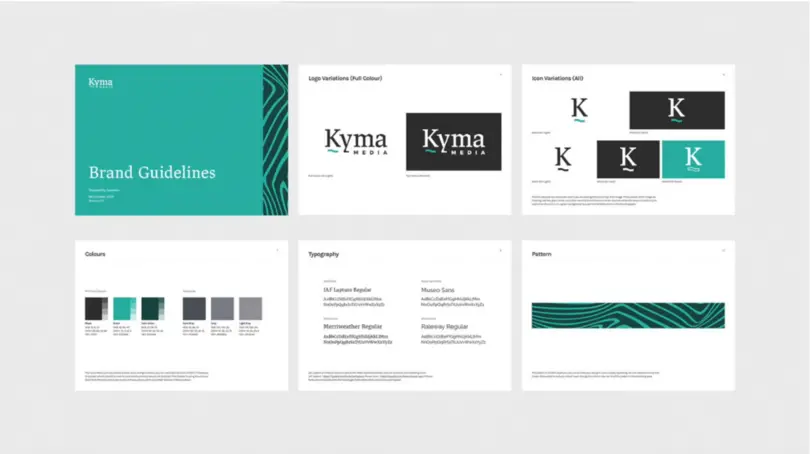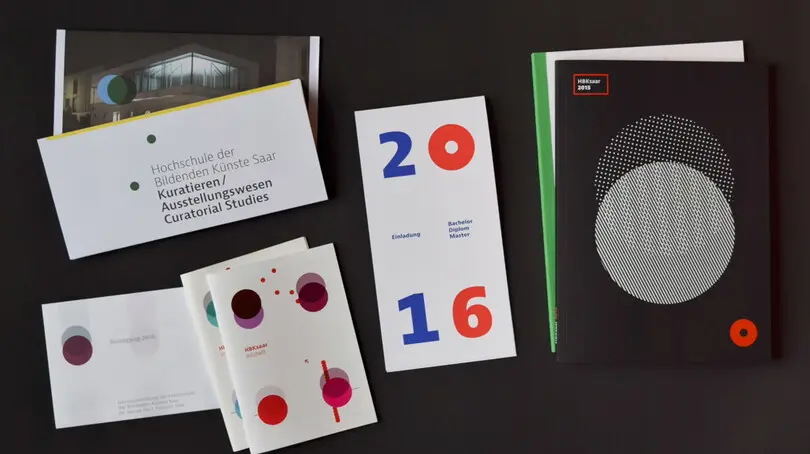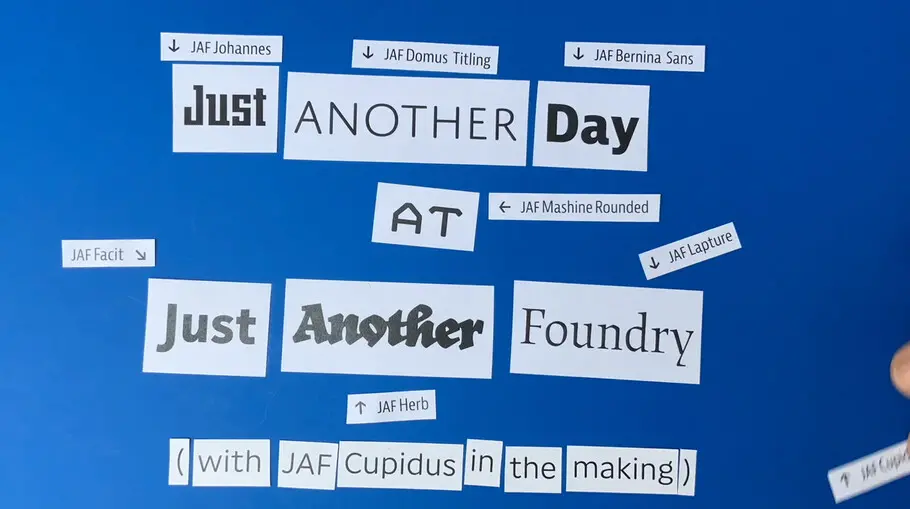
組織のメッセージを企業の声として伝えるツール
コーポレートフォント(企業専用書体)
ドイツのミュンヘンでティム・アーレンス氏とタイプファンダリー「Just Another Foundry」(以下、JAF)を運営し、書体開発や欧文組版の仕事をされている麥倉聖子氏のプレゼンテーション。武蔵野美術大学卒業後、イギリスのレディング大学で欧文タイポグラフィを学びました。
今回のテーマであるコーポレートフォント(企業専用書体)は、組織のメッセージを伝えるツールで、いわばその企業の声のようなもの。欧州でも広く使われており、ドイツではメルセデスベンツやルフトハンザなどが有名です。企業や組織のブランドアイデンティティを決めるときにデザインの一環として特定の書体を指定して、すべてのマーケティングに使うことが一般的になっています。
セッションの冒頭では、JAF が制作したフォントやコーポレートフォントを紹介。
Kyma Media Branding のコーポレートフォントには、JAF Lapture というブラックレターを取り入れた書体が使われています。
また、お茶のブランド Klenk では、ラウンドサンズの JAF Domus を使用。企業ロゴだけでなく、Webサイトやカタログ、説明文にも使われているそうです。
Germany Trade & Invest ドイツの経産省 GTAI のアイデンティには、JAF Bernina Sans とニュージーランドの書体デザイナー、クリス・ソワーズビーさんの書体 Tiempos を使用。
ドイツの美術大学 HBKsaar のアイデンティティ。JAF Bernina Sans を専用書体として使用。かっこよく使ってくれていて、制作物を見るのが楽しみだそうです。
コーポレートフォントの利用は欧州ではとても一般的。大企業に限らず浸透しているそうです。しかし、コーポレートフォントがあるから大丈夫というわけではありません。コーポレートフォントを見つけることは、結婚するパートナーを見つけることに似ています。結婚式と結婚生活が違うように、コーポレートフォントを見つけることと運用することは別問題なのです。
コーポレートフォントの運用の問題点はこちらの4点。
1. コーポレートフォントと全然合わないシステムフォントを併用して使っている
2. 新旧フォントが混在
3. 印刷物はがんばっているのに Webサイトにはフリーフォントを使っている
4. 組版に問題あり
1は運用する人がデザイナーではない場合、専用書体ですべてカバーできない場合(例えば、長文で使えないなど)に起こる問題。運用が始まる前にシステムフォントを決めておくとよいそうです。
2は比較的大きな組織で、アートディレクターがいない場合によく起こる問題。
3は Webフォントの初期にはユーザーが使いたくても価格的に手が出なかったこともありましたが、今は価格的に安定したこと、オンラインマーケティングの重要性が理解されてきたこともあり、改善されつつあります。
4はいろいろなケースが見られます。
• 字間や単語間のスペーシングの設定がまずい(字間が空きすぎ、単語間がつまりすぎ)
• 行間や行長の設定がまずい(行間が詰まりすぎ、行が長すぎ)
• 行末処理ができておらず、ガタガタで読みにくい(行末が飛び出している、1単語残ってしまっている)
• リガチャー(合字)やコンテクスチュアル・オルタネート(文脈に応じて別の文字に自動的に切り替わって表示される機能)が使いこなせていない
• 書体のチョイスが組まれた文章のチョイスにあっていない
• ダーシや引用符の間違った使用(間抜け引用符、ダーシのかわりにハイフンが使われている)
• 大文字、小文字の使い分けの間違い(人名が全部大文字になっているなど)
• ハイフンの位置の設定が間違っている(child-like なのに chil-dlike で切れている)
欧文組版のミスをさらに細かく分別すると、以下の3タイプに分けられます。
A:欧州の組版初心者でも絶対にしないミス
• 大文字小文字の使い分けの間違い(小学校で習うのでネイティブは間違えない)
• ハイフンの位置の間違い(ソフトウェア上で自動設定されているので間違えない)
B:欧州の組版初心者がよくするミス
• ダーシや引用符の間違った使用
• イタリックの間違い
• 行末処理がガタガタ
• 書体のチョイスにもう一工夫
C:欧州のデザイナーでもしてしまうミス
• 字間や単語間の設定がまずい
• 行間、行長の設定がまずい
• リガチャーやコンテクスチュアル・オルタネートが使えていない
Aは表記法の領域、Bは見た目の領域に近く、同じミスでもAのミスとBのミスは質が違います。Cは経験を積むうちにうまくなります。
重要なポイントをまとめると、読み手にとって重要なのはAの表記法の領域のミス。ここがクリアできないと専用書体を使っていても現地の人は絶対に「おかしい」と気づきます。
そこを最低のボーダーラインとして覚えておくとよいでしょう。
イギリスとドイツのタイポグラフィの傾向の違いはありますか?
(麥倉氏)ドイツの方が組版のレベルが高いように思います。学校でスキルを身につけてから社会に出ているからでしょうか。イギリスの大学はアート寄りのところが多いのが原因かもしれません。
(小林)同感です。ドイツの地方紙の記者が書体のことをすごくよく知っていました。一般人レベルでもよく知っていますね。
グラフィック寄りの仕事でも組版には気をつけるべきでしょうか?
今回は文章、本文組のお話をしましたが、ポスターや広告などは別です。ルールにとらわれずに自由に制作していいと思います。
欧文書体を学ぶにあたり感銘を受けた書籍は?
(麥倉氏)どれが一冊というのはないのですが、東ドイツのタイポグラファー、アルバート・カパの本がいいですね。
(小林)本よりも街中で見かける文字、手を使って生み出したものの力はすごいと思います。なぜ Type& で石彫やカリグラフィの話をするのかと言うと、定規を使わず有機的な線を出すとどう見えるのかを考えている人が話す言葉には説得力があるからです。普段から目を使って見ていると、目が鍛えられているから気づく。文字の見え方に対するセンスを養うことにつながります。本を読んだからわかるということではないのです。
(麥倉氏)3年くらい前からカリグラフィを始めてみて、もっと理解することができました。すぐうまくならないかもしれませんが、目が鍛えられます。
(小林)文字の中に宿る力、定規を使わないで書くと何が違うのか。麥倉さんの文章の組み方は、コンピュータに流し込んでおしまいではありません。そこから先に何をするのか? 「ちょっとおかしいな?」と判断する目を養うために、手を動かして字を書いてみる。ちょっと考えてみる。一回立ち止まってみると、目を鍛えるための一歩になります。そうしたことが Type& のセッションから伝わればいいなと思っています。